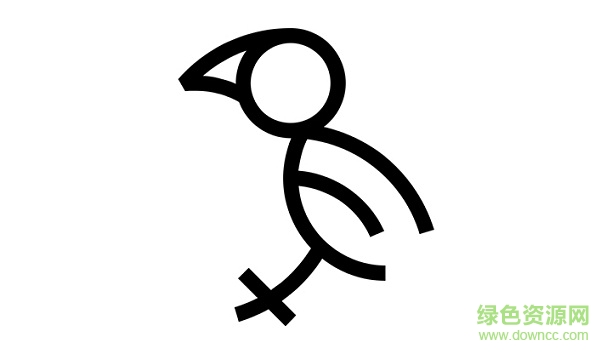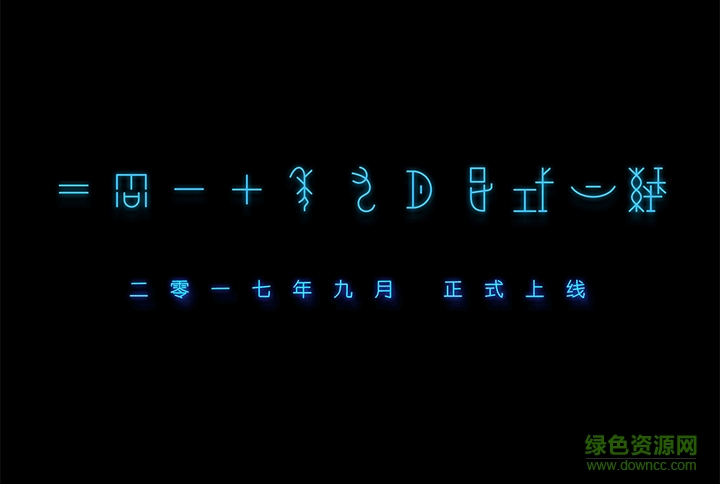
漢儀甲骨文字體是一款漢儀字體,甲骨文字體古典氣息十足,該字體能幫助您輕松學習甲骨文,還適合logo標題的設計,好看字體下載盡在綠色資源網!
史上最具 Bigger 的甲骨文字庫來襲!這一次,無論你是時尚屆的,還是美(chī )食(huò)圈兒的,又或者是運動達人,甚至是東西南北各行各業(yè)...只要你夠創(chuàng)意,讓我們一起玩兒轉古漢字!
漢儀甲骨文字體是一款結合古代字體的時尚字體,創(chuàng)新傳承,擁抱變化,這一次,讓古漢字在我們面前,閃閃發(fā)光。